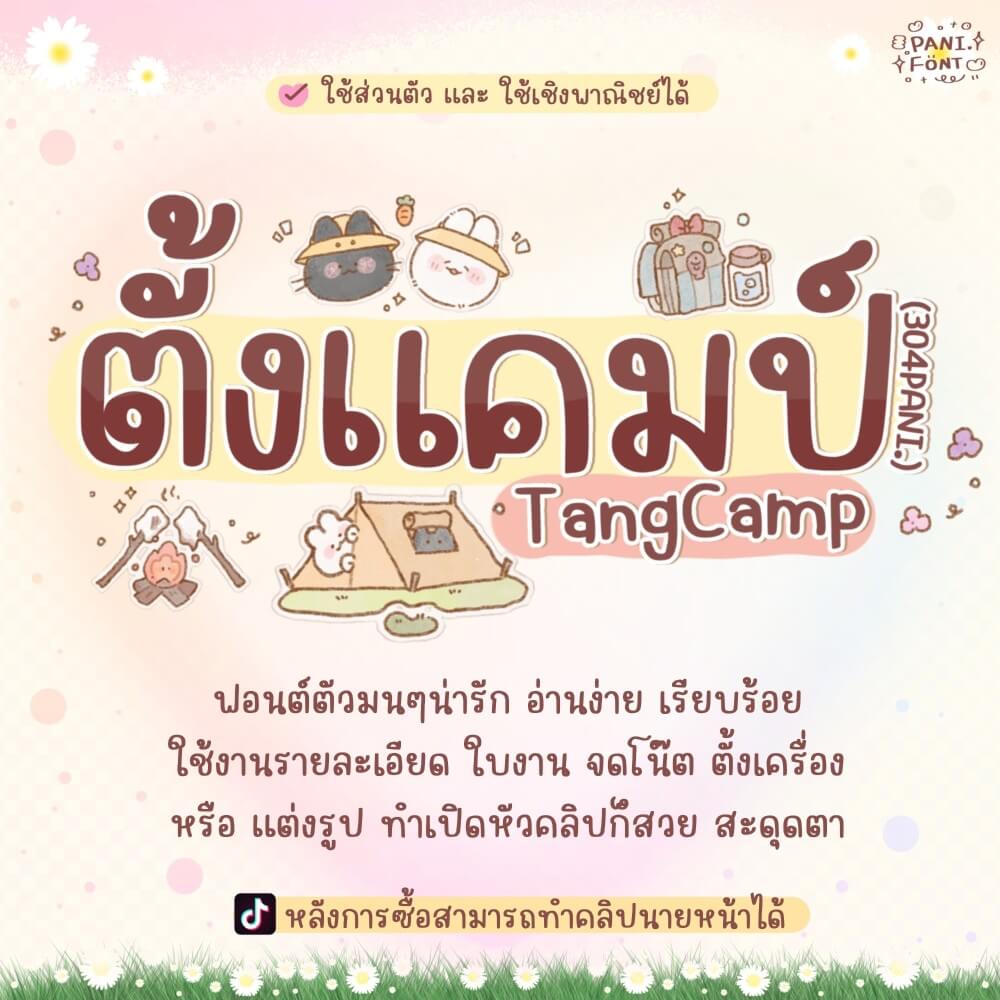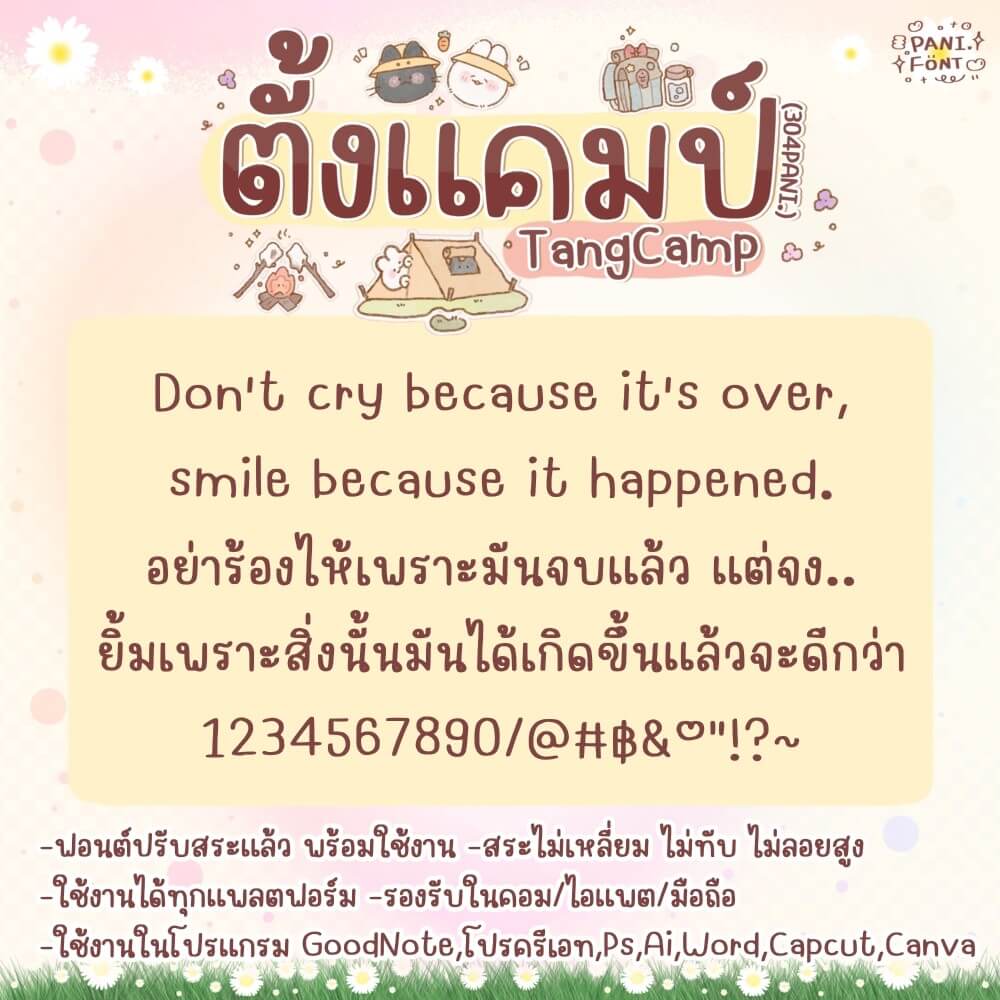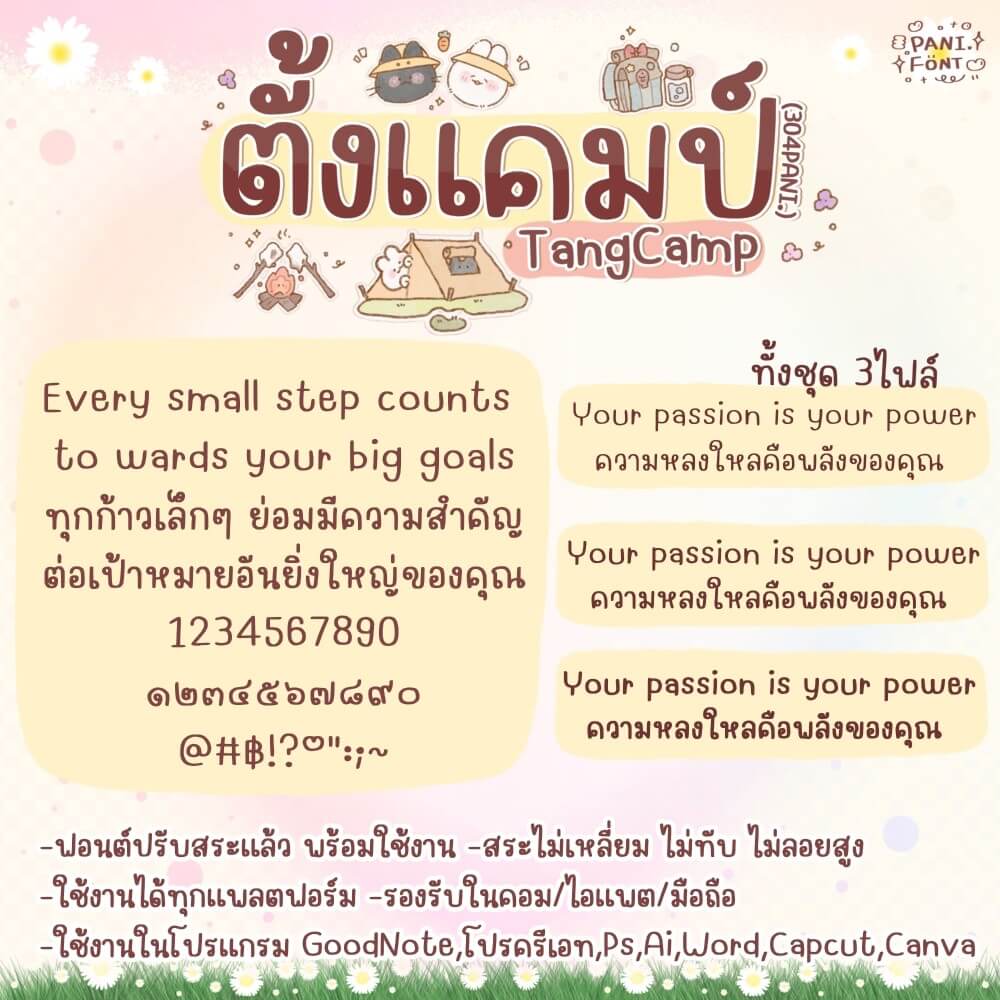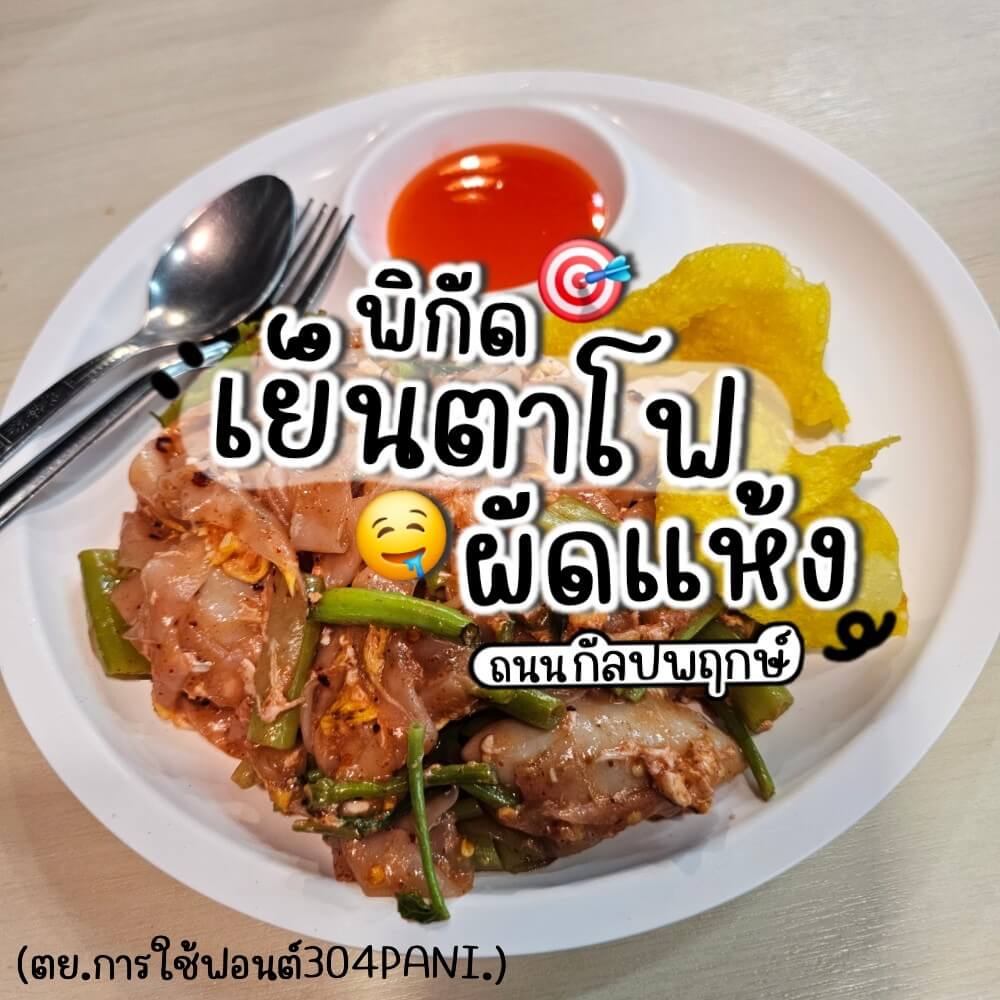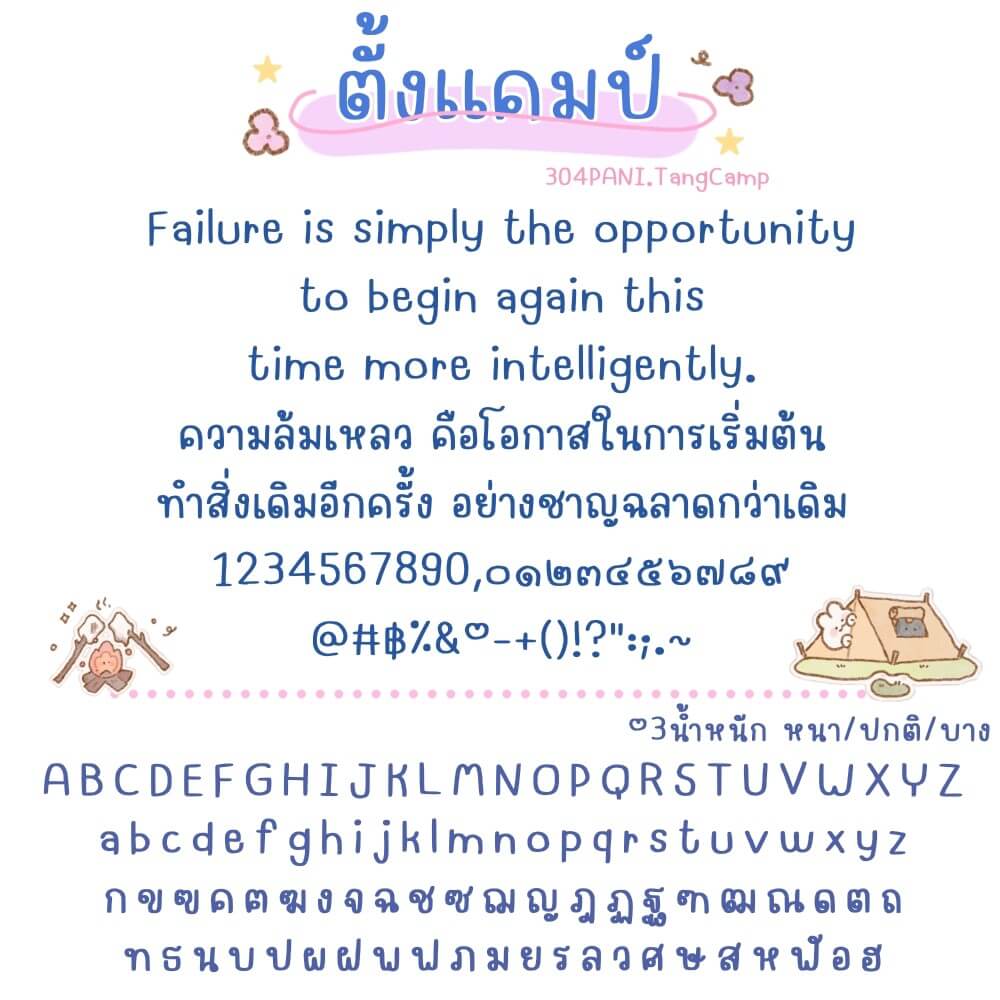
ฟอนต์ 304PANI.ตั้งแคมป์ – ฟอนต์ตัวมนๆ น่ารัก อ่านง่าย เรียบร้อย ใช้งานรายละเอียด ใบงาน จดโน้ต ตั้งเป็นฟอนต์เครื่อง หรือแต่งรูป ทำเปิดหัวคลิปก็สวย สะดุดตา
304PANI.ตั้งแคมป์